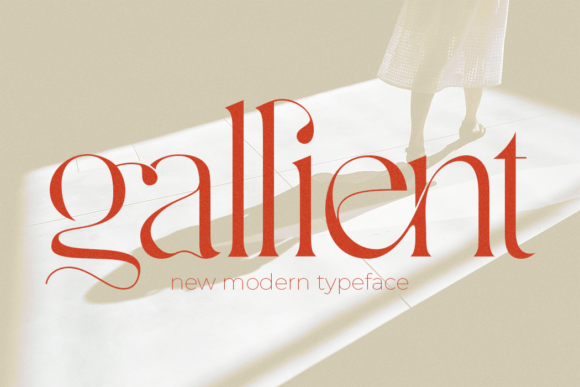
Gallient - элегантный шрифт serif.
Этот шрифт является идеальным выбором для любого проекта, требующего чистых, современных, минималистичных, элегантных и красивых дизайнерских стилей.